이름이 짧으면 싸인을 만들 때 너무 단순해 보일까 봐 걱정되나요? 🤔 하지만 걱정하지 마세요! 짧은 이름도 충분히 세련되고 스타일리시한 싸인을 만들 수 있답니다.
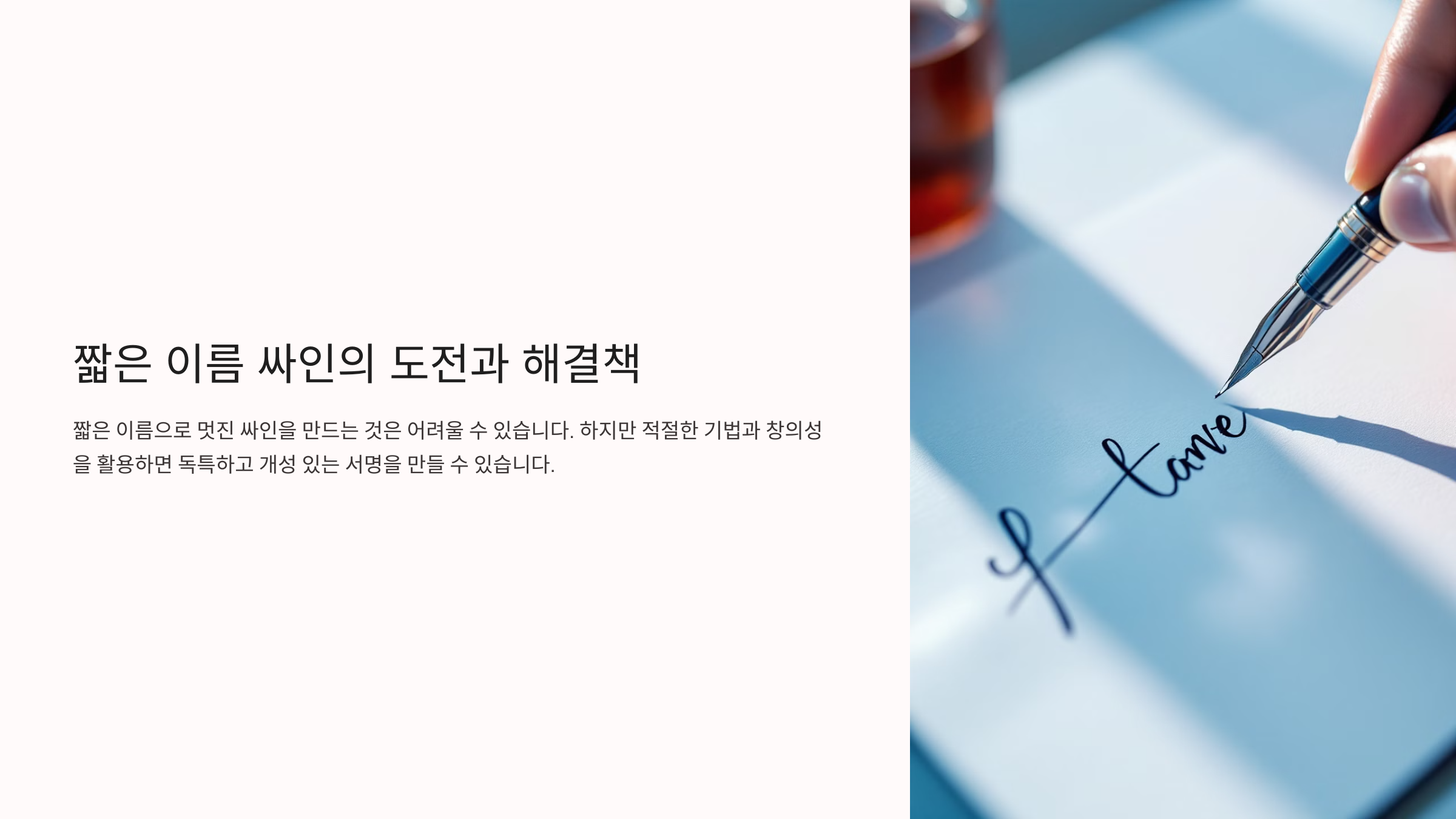
오늘은 짧은 이름을 활용해 더 멋진 싸인을 완성하는 방법을 알려드릴게요! 🚀
짧은 이름 싸인이 어려운 이유 🤔
이름이 짧으면 싸인이 단순해 보일 가능성이 높아요. 특히 2~3글자 정도의 짧은 이름은 디자인할 요소가 많지 않아서 독창적인 스타일을 만들기 어렵다고 느낄 수 있어요.📌 짧은 이름 싸인의 어려움
문제점 설명 단순한 디자인 이름이 짧으면 싸인이 밋밋해 보일 수 있어요. 차별화 어려움 비슷한 스타일이 많아 독창적인 디자인이 어렵죠. 공백 문제 싸인이 너무 작아 보이거나, 공간이 남을 수 있어요. 하지만 걱정할 필요 없어요! 짧은 이름도 스타일을 더하면 충분히 멋진 싸인이 될 수 있답니다. 그럼 짧은 이름을 멋지게 바꾸는 3가지 스타일을 알아볼까요? 😆
짧은 이름을 멋지게 만드는 3가지 스타일 ✨
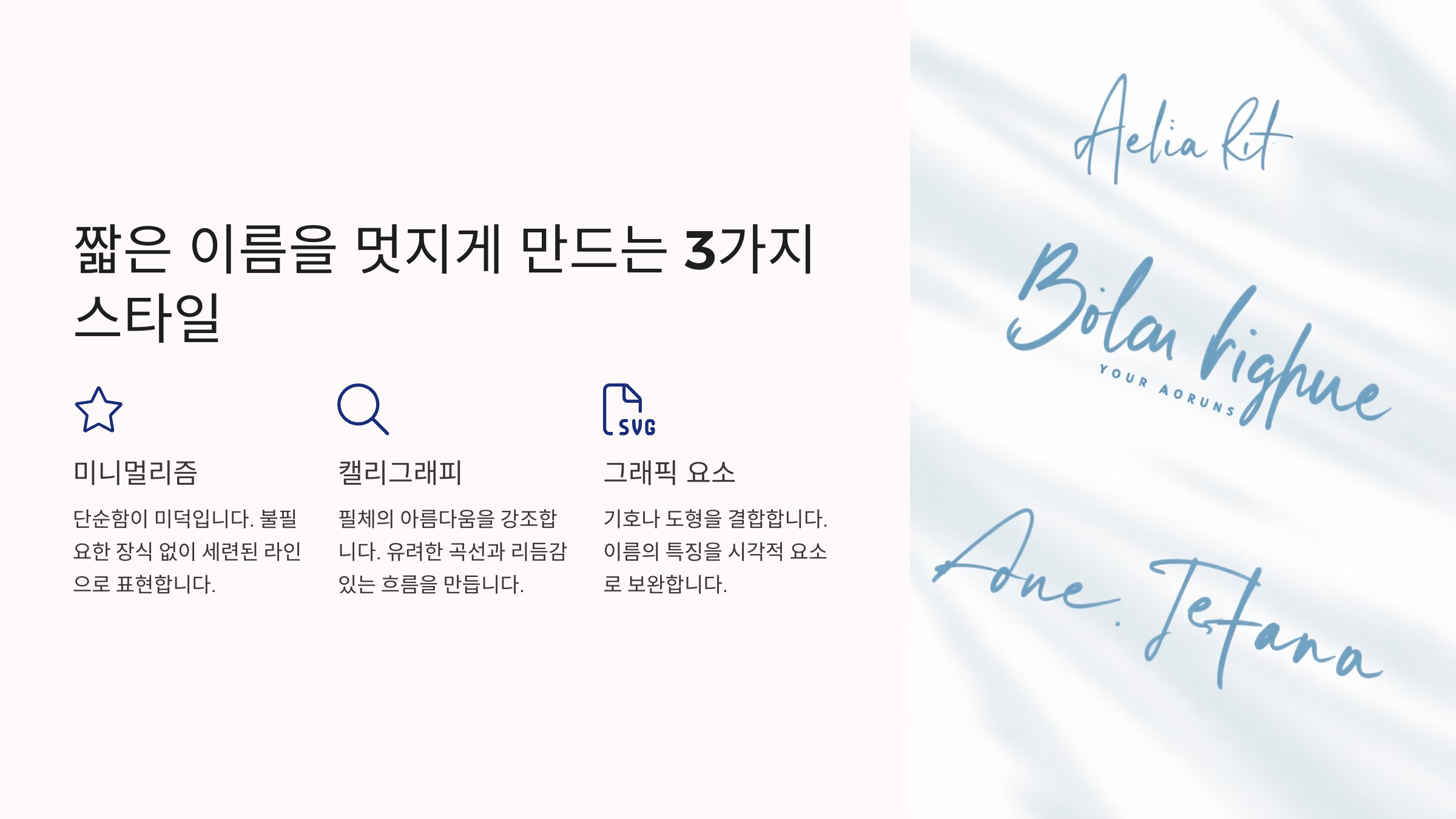
짧은 이름도 디자인 요소를 활용하면 충분히 멋지고 개성 있는 싸인을 만들 수 있어요. 다음 3가지 스타일을 활용하면 더 세련된 느낌의 싸인을 완성할 수 있답니다! 😊
📌 짧은 이름 싸인 스타일 3가지
스타일 특징 추천 대상 이니셜 강조 이름의 첫 글자를 크게 쓰거나 변형하는 방식 심플하면서도 강렬한 인상을 주고 싶은 사람 곡선형 디자인 이름을 부드러운 필기체로 연결하는 스타일 부드럽고 세련된 느낌을 원할 때 기호 활용 밑줄, 점, 별 등의 기호를 추가해 포인트를 주는 방식 더 개성 있는 싸인을 원할 때 이제 기본적인 스타일을 알았으니, 이니셜을 활용하는 방법도 알아볼까요? 😆
이니셜 활용법 🔠
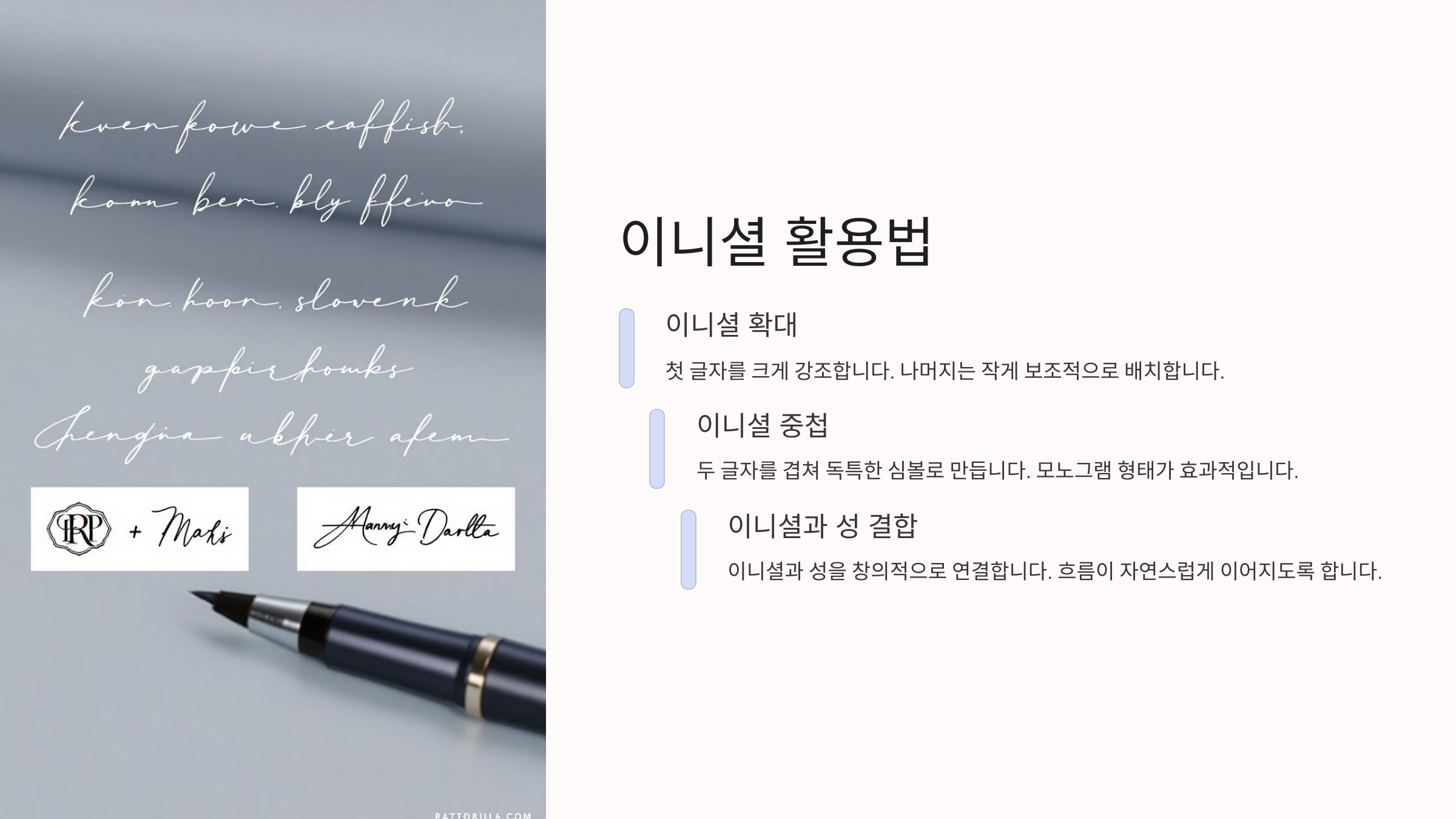
이니셜(첫 글자)은 싸인의 가장 중요한 요소 중 하나예요. 짧은 이름이라면 이니셜을 강조해서 독창적인 싸인을 만들 수 있어요!
📌 이니셜을 활용하는 3가지 방법
- ✔ 이니셜을 크게 강조 → 싸인의 시작을 강렬하게 만들 수 있어요.
- ✔ 이니셜을 변형 → 곡선이나 직선을 활용해 독창적인 디자인을 만들어요.
- ✔ 이니셜을 연결 → 다음 글자와 자연스럽게 이어서 세련된 느낌을 줄 수 있어요.
이니셜만 잘 활용해도 짧은 이름을 더 인상적인 싸인으로 만들 수 있어요. 그럼 기호를 활용하는 방법도 알아볼까요? 😊
기호를 활용한 싸인 디자인 ✨
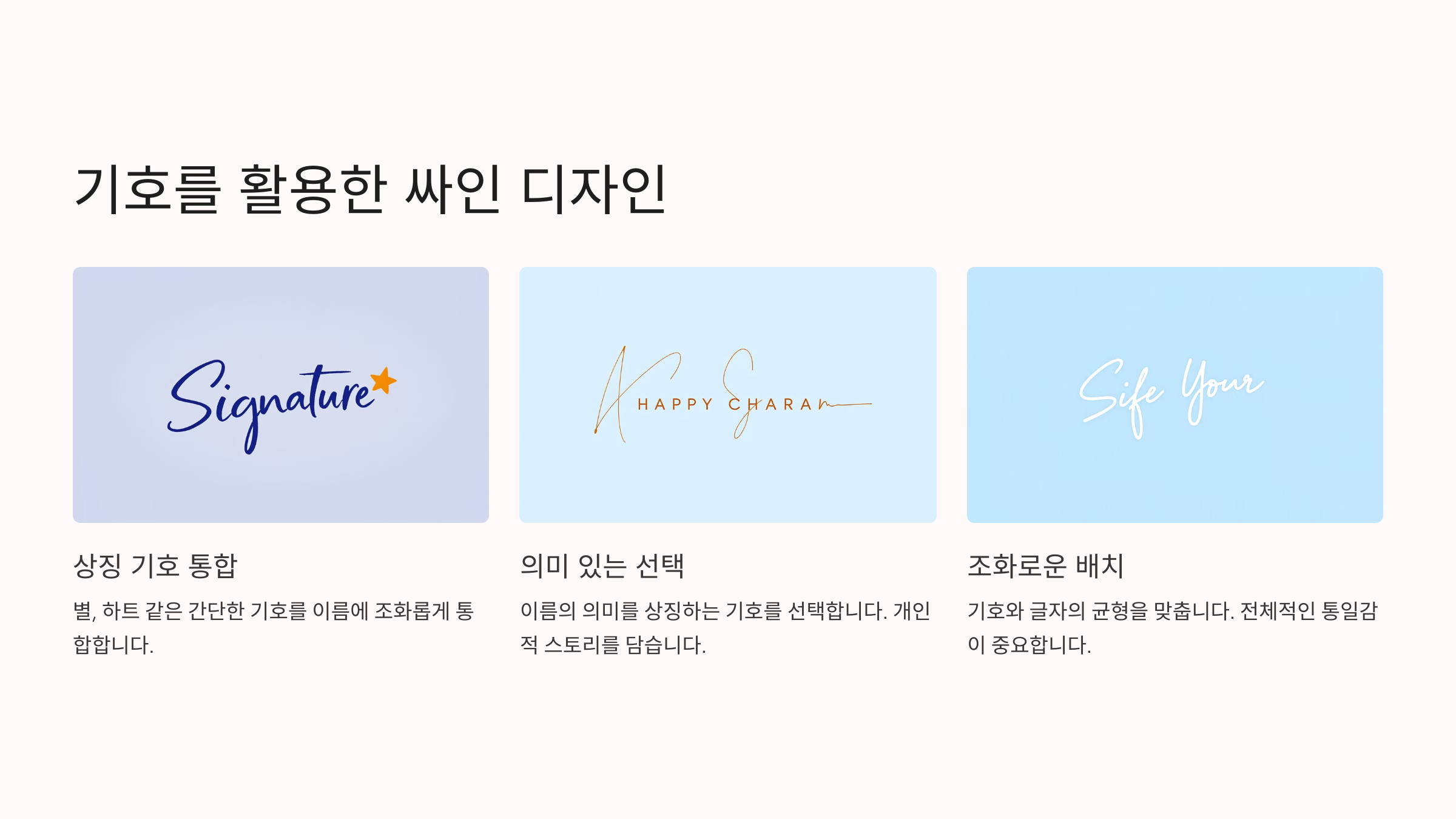
싸인이 너무 짧거나 단순해 보일 때는 기호를 활용하면 개성을 살릴 수 있어요! 적절한 기호를 추가하면 싸인이 더 세련되고 독창적인 느낌을 줄 수 있답니다. 😆
📌 싸인에 활용하면 좋은 기호 4가지
기호 활용 방법 ⭐ 별 싸인의 끝에 넣어 개성을 살릴 수 있어요. __ 밑줄 이니셜이나 이름 전체를 강조할 때 유용해요. • 점 싸인의 흐름을 부드럽게 만들거나 마무리를 세련되게 연출할 수 있어요. ↗ 화살표 상승하는 느낌을 주어 역동적인 스타일을 연출할 수 있어요. 이제 싸인에 어떤 기호를 활용하면 좋을지 알았어요! 그럼 균형 잡힌 싸인 디자인을 만들기 위한 방법도 알아볼까요? 🤩
균형 잡힌 짧은 싸인 만들기 ⚖
짧은 이름일수록 글자의 크기와 배치를 조절해서 균형을 맞추는 것이 중요해요. 글자가 너무 작아 보이거나 한쪽으로 치우치지 않도록 적절한 공간 배분을 해보세요!
📌 균형 잡힌 싸인을 위한 3가지 방법
- ✔ 이니셜을 강조하라 → 이름이 짧으면 첫 글자를 더 크게 만들어 포인트를 줄 수 있어요.
- ✔ 공간을 활용하라 → 싸인이 너무 작아 보이지 않도록 적절한 크기로 조절하세요.
- ✔ 곡선과 직선을 조합하라 → 부드러운 곡선과 강한 직선을 조합하면 더 세련된 싸인이 돼요.
이제 균형 잡힌 싸인을 만드는 방법도 알았어요! 그럼 실제로 유명인의 짧은 싸인 스타일을 분석하면서 더 많은 영감을 얻어볼까요? 😊
유명인의 짧은 싸인 스타일 분석 🌟
짧은 이름을 가진 유명인들은 어떻게 싸인을 만들었을까요? 그들의 싸인을 분석하면 짧은 이름도 충분히 스타일리시한 싸인을 만들 수 있다는 것을 알 수 있어요. ✍
📌 유명인의 짧은 싸인 스타일 비교
유명인 싸인 스타일 특징 엘론 머스크 이니셜 + 곡선형 이니셜을 강조하면서 자연스러운 흐름을 살림 코비 브라이언트 직선적이고 강렬한 디자인 짧지만 힘 있는 획을 활용해 독창적인 싸인 완성 지드래곤 (G-Dragon) 이니셜 + 기호 활용 별(⭐)과 선을 활용해 개성 있는 스타일 연출 제이 지 (Jay-Z) 필기체 스타일 부드러운 곡선과 연결된 글자로 우아한 느낌 이처럼 짧은 이름도 디자인 요소를 잘 활용하면 독창적인 싸인을 만들 수 있어요! 그럼 마지막으로 짧은 이름 싸인과 관련된 FAQ를 살펴보면서 궁금증을 해결해 볼까요? 😊
FAQ ❓
Q1. 이름이 너무 짧아서 싸인이 밋밋해 보일 때 어떻게 하면 좋을까요?
A1. 이럴 때는 이니셜을 변형하거나 기호를 추가하면 개성을 살릴 수 있어요! 예를 들어, 첫 글자를 더 크게 강조하거나, 점(•), 밑줄(__), 별(⭐) 등을 활용해 보세요. ✨
Q2. 짧은 이름 싸인을 더 멋지게 만들기 위한 가장 쉬운 방법은?
A2. 가장 쉬운 방법은 이니셜을 변형하는 것이에요. - 첫 글자를 크게 쓰거나 기울여서 스타일을 강조하세요. - 곡선을 추가해 부드러운 흐름을 만들면 더욱 세련돼 보일 수 있어요. 😊
Q3. 짧은 싸인이 너무 단순해 보일 때 어떤 요소를 추가하면 좋을까요?
A3. 싸인에 기호나 밑줄을 추가하면 단순함을 보완할 수 있어요. 예를 들어, 마지막 획을 길게 빼거나, 별(⭐)이나 점(•)을 활용하면 싸인이 더 감각적으로 보일 수 있어요. 🎨
Q4. 싸인을 만들 때 균형을 맞추는 가장 좋은 방법은?
A4. 싸인을 디자인할 때 글자의 크기와 간격을 조절하는 것이 중요해요. - 이니셜을 강조하고 나머지 글자를 상대적으로 작게 조정하세요. - 너무 한쪽으로 치우치지 않도록 균형을 맞춰 배치하세요. ⚖
Q5. 싸인에서 글자를 기울이면 어떤 효과가 있나요?
A5. 글자를 기울이면 역동적인 느낌을 줄 수 있어요. - 오른쪽으로 기울이면 더 활동적인 인상을 줄 수 있고, - 수평을 유지하면 차분하고 안정적인 느낌을 줄 수 있어요. 🔄
Q6. 짧은 이름을 활용한 싸인에서 가장 중요한 포인트는?
A6. 가장 중요한 포인트는 이름이 짧은 만큼 개성을 강조하는 것! ✔ 이니셜을 강하게 변형하거나, ✔ 마지막 획을 길게 빼서 디자인 요소를 추가, ✔ 기호(⭐, __, • 등)를 활용해 독창적인 스타일을 만들면 좋습니다! 😆
Q7. 유명인의 짧은 싸인에서 배울 수 있는 점이 있을까요?
A7. 네! 유명인들의 싸인을 보면 이니셜 활용, 기호 추가, 획 변형 등 다양한 스타일을 적용하고 있어요. 그들의 싸인을 참고하면서 나만의 개성을 살린 싸인을 디자인해보세요! ✍
Q8. 짧은 이름을 싸인으로 만들 때 가장 피해야 할 점은?
A8. 가장 피해야 할 점은 너무 단순하거나 가독성이 떨어지는 디자인을 만드는 것! ✔ 너무 작고 밋밋한 디자인은 피하세요. ✔ 획이 너무 많거나 복잡하면 읽기 어려울 수 있어요. ✔ 적절한 크기와 개성을 유지하는 것이 중요해요! 😉
짧은 이름도 스타일과 디자인 요소를 추가하면 충분히 멋진 싸인이 될 수 있어요! ✔ 이니셜 변형 ✔ 기호 활용 ✔ 글자 크기와 배치 조절 이 세 가지만 기억하면 더 독창적이고 스타일리시한 싸인을 만들 수 있습니다! 🚀